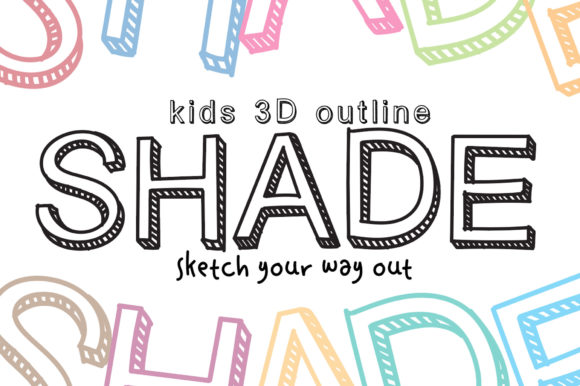
Kids 3D Outline Shade
Kids 3D Outline Shade – A Fonte Que Transforma Seu Conteúdo Infantil
Se você procura uma tipografia divertida, colorida e super versátil para projetos infantis, a Kids 3D Outline Shade é a escolha ideal. Com um estilo cartunesco e contorno sombreado em 3D, essa fonte traz vida instantânea a quadros de giz, cartazes educativos, convites de festa e qualquer material de ensino que precise de um toque lúdico.
Por que escolher Kids 3D Outline Shade?
- Design autêntico e realista – O efeito de sombra tridimensional cria a sensação de profundidade, como se as letras fossem recortadas de papel ou giz.
- Facilidade de leitura – Apesar do visual “desenhado”, os caracteres mantêm boa legibilidade, perfeito para crianças em idade pré‑escolar e fundamental.
- Versatilidade de uso – Ideal para:
- Quadros de avisos e quadros negros;
- Materiais didáticos (folhas de atividade, livros de cores, cartazes de alfabetização);
- Convites, banners e flyers de festas infantis;
- Posts de redes sociais voltados ao público infantil.
A Kids 3D Outline Shade não é apenas uma fonte; é uma ferramenta de comunicação que traz personalidade, diversão e clareza visual a qualquer projeto voltado ao público infantil. Experimente hoje mesmo e veja como suas criações ganham um toque mágico que encanta professores, pais e, claro, crianças!